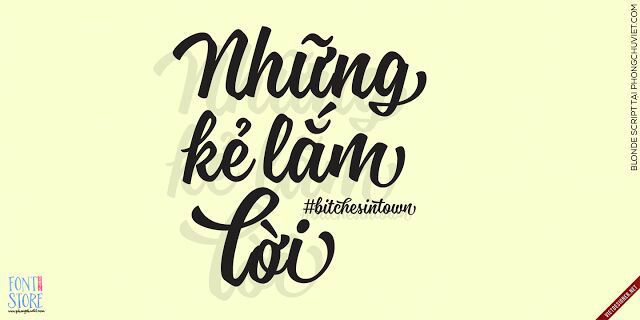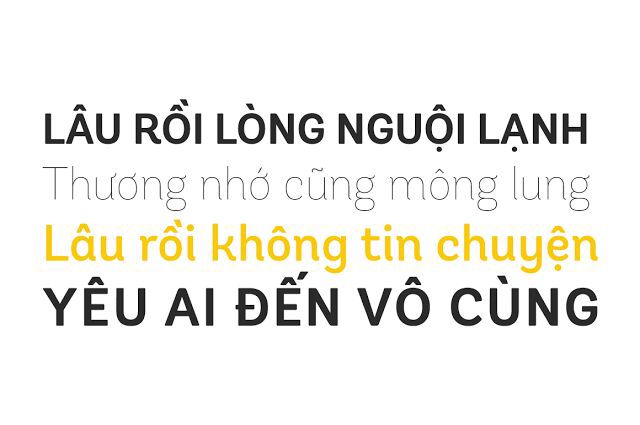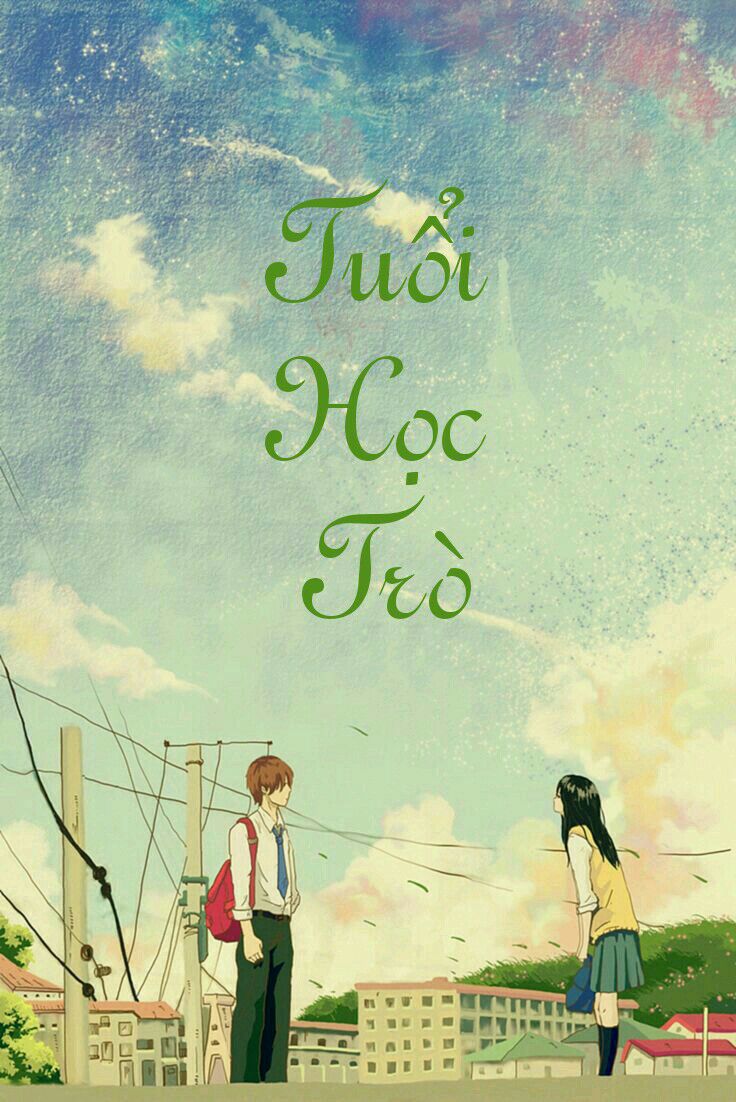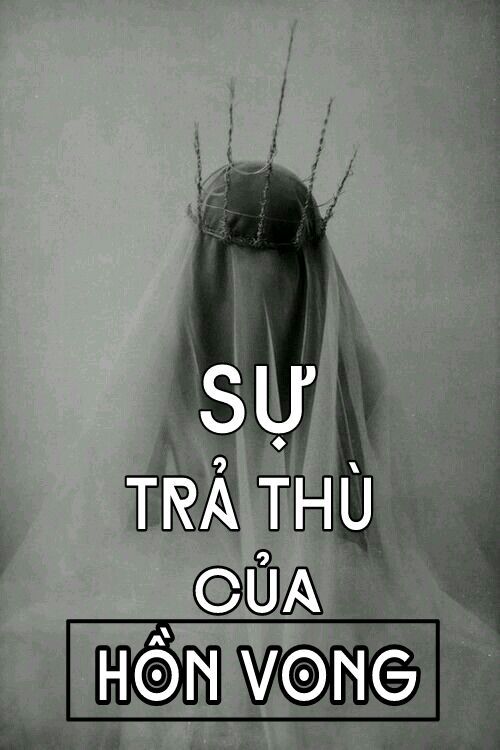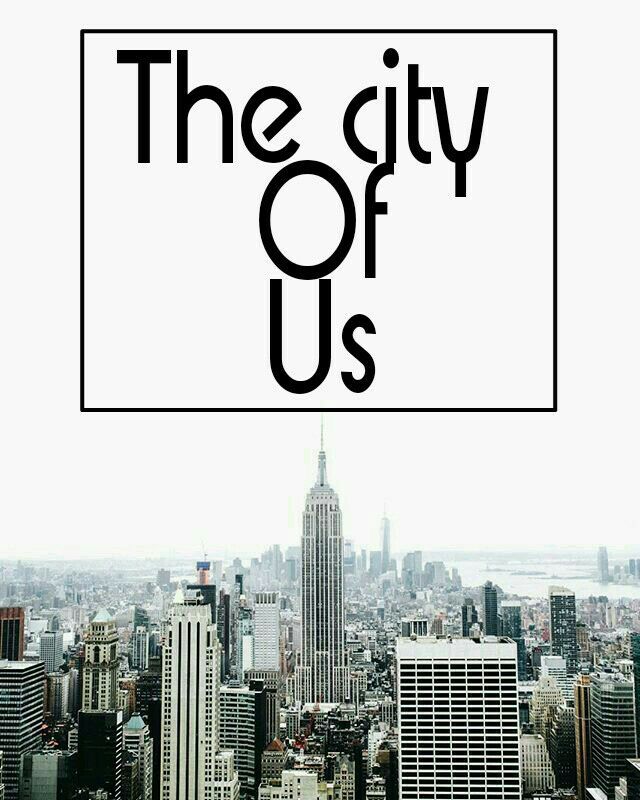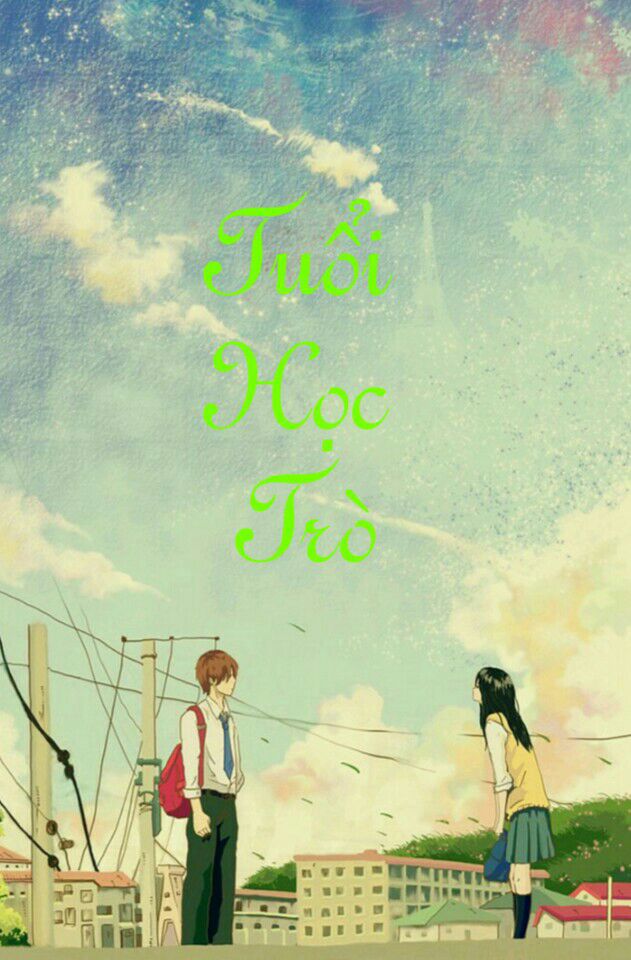
Trước tiên khi làm một designer, các cậu hãy chú ý đến định nghĩa một chút nha! Trước tiên là font với typeface!
1. Typeface và font.
Typeface hay còn gọi là Font family, kiểu chữ, là một bộ các chữ cái có cùng điểm chung trong thiết kế. Nói cách khác, mỗi typeface là tập hợp các ký tượng, mỗi ký tượng đại diện cho một chữ cái, số, dấu câu và các biểu tượng khác. Như trên đã nói, typeface khác với font, điều sẽ trở nên rõ ràng hơn khi đề cập đến định nghĩa.
a. Serif (font cứng)
Serif typeface là loại typeface có các nét phụ ở cuối các nét chính của chữ. Serif dịch nôm na ra là chân của chữ.
Ví dụ:
b. Sans Serif (font cứng)
Sans serif nghĩa là không có serif.
Ví dụ:
c. Script (hay còn gọi là font mềm)
Script là kiểu chữ bắt chước chữ viết tay. Thường sử dụng các nét uốn lượn. Các kiểu chữ này không thích hợp sử dụng trong phần thân văn bản, vì nó rối mắt và khó đọc hơn các kiểu serif và sans serif.
Ví dụ:
Đó là những loại font cơ bản của designer.
2. Color
Màu sắc cũng góp phần quan trọng trong việc 1 bức tranh có đẹp hay không? Cũng chính vì thế mà rất nhiều designer mắc lỗi trong khâu này.
a. Bảng màu
b. Chọn màu
Nhiều designer chọn blend màu rất tệ. Tức là chọn blend màu quá nổi, quá chói! Kiểu như mấy bạn ấy chọn màu đỏ mà sáng chói, blend 100% luôn! Chọn màu nằm ngoài cùng của vòng tròn như trên hình á! Thực sự mà nhìn vô muốn đập nát cái máy! Như thế này nè!
Vậy còn pic này!
*Hình ảnh chỉ mang tính chất minh họa, không phải là pic để đưa ra nhận xét.*
Vậy blend màu nào đẹp hơn, tất nhiên là cái thứ 2. Màu sắc pic 2 hợp với hình hơn, blend màu đơn giản: 45% xanh, 55% đen.
Còn pic thứ nhất: 100% xanh nhìn rất là chói mắtm dẫn tới ảnh không hề có gì gọi là hồn hết. Nhìn cứ như đang hỏng cả bức ảnh á! Hồi trước Miu có đi qua một team, nhìn thấy một bạn designer dùng blend màu hồng đỏ chót, tất nhiên clickback ngay lập tức rồi!
Chúng ta cần phải phối hợp màu cho hợp với chủ đề, blend màu không quá nổi! Chỉ cần các bạn đừng phối như kiểu pic 1 mà hãy phối hợp với những màu đen rồi chọn sắc độ phù hợp là được!
c. Trắng/đen
Hai color này có lẽ là 2 màu dễ phối nhất. Hay còn gọi là màu trung gian, nó có thể phối với tất cả những blend màu khác, nhưng bạn nghĩ sao nếu nó không được sử dụng đúng chỗ?
Kiểu như ảnh đen xám thì sử dụng font trắng, ảnh đỏ trắng thì sử dụng font đen. Nó thực sự làm cho ảnh không có hồn, thay vào đó là rối, màu không khớp với ảnh.